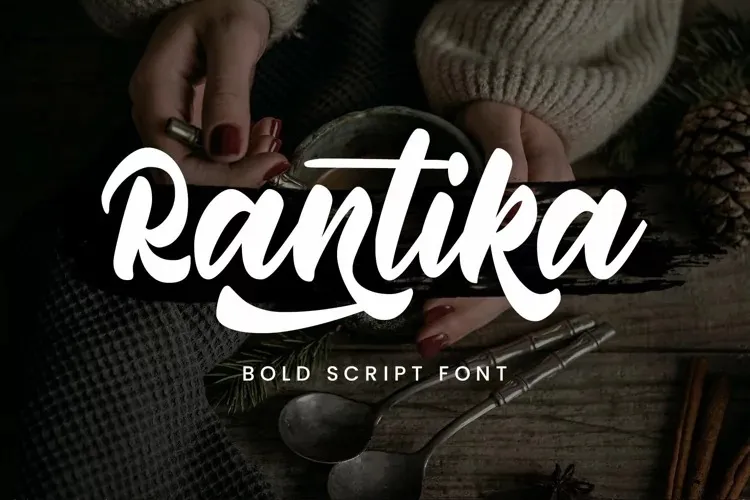
A Rantika Font é uma elegante e moderna fonte script criada pelo Arterfak Project. Suas linhas fluidas e estilo chamam atenção por sua sofisticação moderna, mas mantêm um ar descontraído com seu toque casual e autêntico. Desenvolvida a partir de traços realizados à mão, essa fonte possui uma espessura de traço informal que dá ao texto uma aparência natural e envolvente. Perfeita para projetos que buscam um equilíbrio entre elegância e desprendimento, Rantika Font é ideal tanto para gráficos profissionais quanto para criações pessoais. Que tal adicionar um toque moderno e autêntico ao seu próximo projeto?